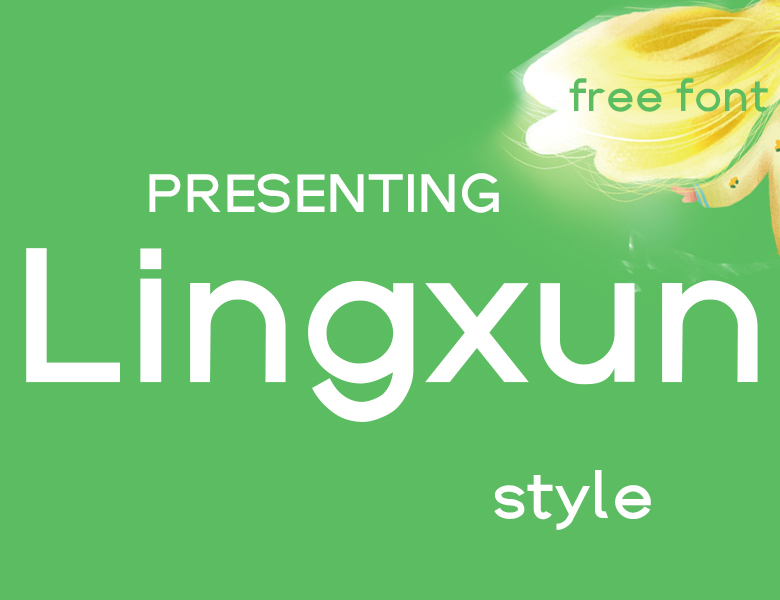
Lingxun style字体
简介:Lingxun-Style是天津的设计师凌旬创作的一款无衬线英文字体,这是一套纯英文字体,包含了Lingxun-style-regular、Lingxun-style-Light和Lingxun-style-bold三种字体(常规,细体与粗体)。免费商业使用。由站长素材提供免费下载,站长字体下载大全提供精选中英文字体素材。